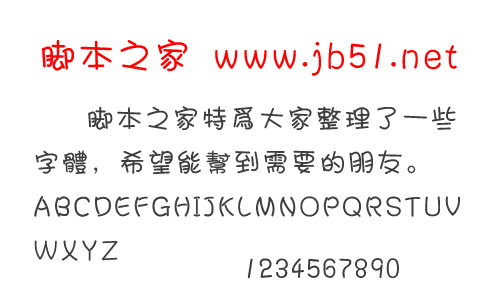
騰祥婀娜體繁是一款非常可愛的POP手繪字體,整幅字風(fēng)格統(tǒng)一、行文規(guī)整,字里行間充滿童真稚趣,彰顯活潑靈動的個性。筆畫圓柔、舒緩隨行、形同婀娜,由設(shè)計(jì)師孔淼手繪完成每個字形的原稿,再由騰祥公司調(diào)整修改完成的美術(shù)體字庫。歡迎喜歡騰祥婀娜體的朋友前來下載使用。